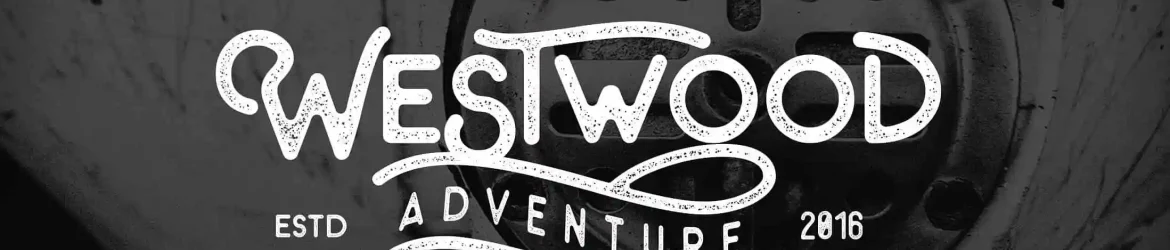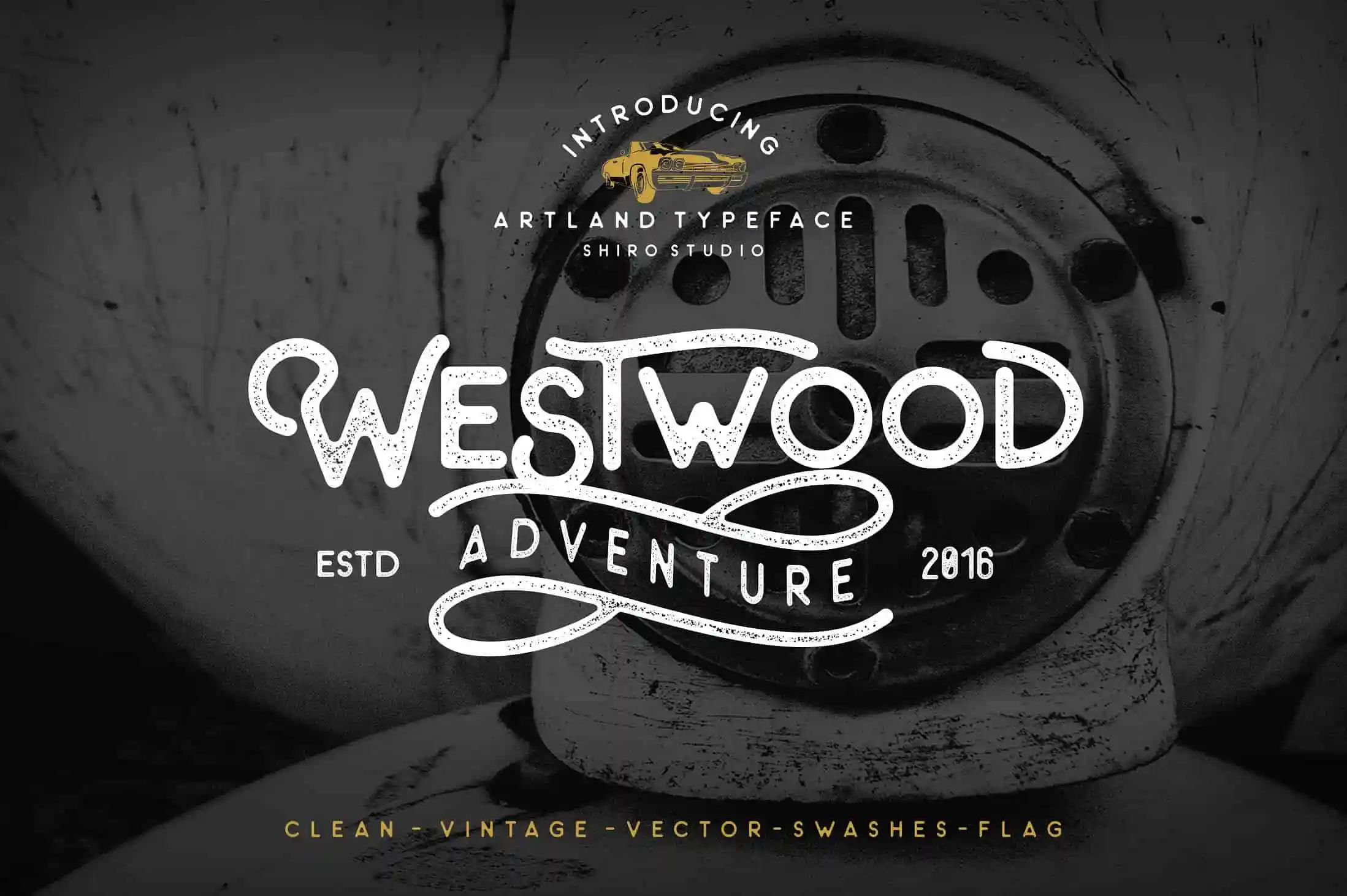
The Artland Typeface – Fonte Grátis
The Artland Typeface
Introduzimos The Artland Typeface! Desenvolvida pelo designer Shiro Std, esta é uma fonte premium vendida na CreativeFabrica, mas está disponível gratuitamente para download hoje. The Artland Typeface é uma tipografia de sans serif estilizada e tem um formato moderno que oferece Clean e Vintage. É perfeito para branding, posters, logotipos e qualquer outro tipo de arte. O uso da fonte The Artland ficará ainda mais interessante ao combinar o alternativo entre minúsculas e maiúsculas e a adição de swashes e pacotes vetoriais. Estas características adicionais podem tornar as suas criações ainda mais atraentes, se preferir jogos de letras alternativas junto com formatos vetorizados. The Artland Typeface é uma escolha segura para quem busca qualidade em um estilo minimalista, ou para aqueles que gostam de incorporar elementos vintage aos seus projetos digitais.